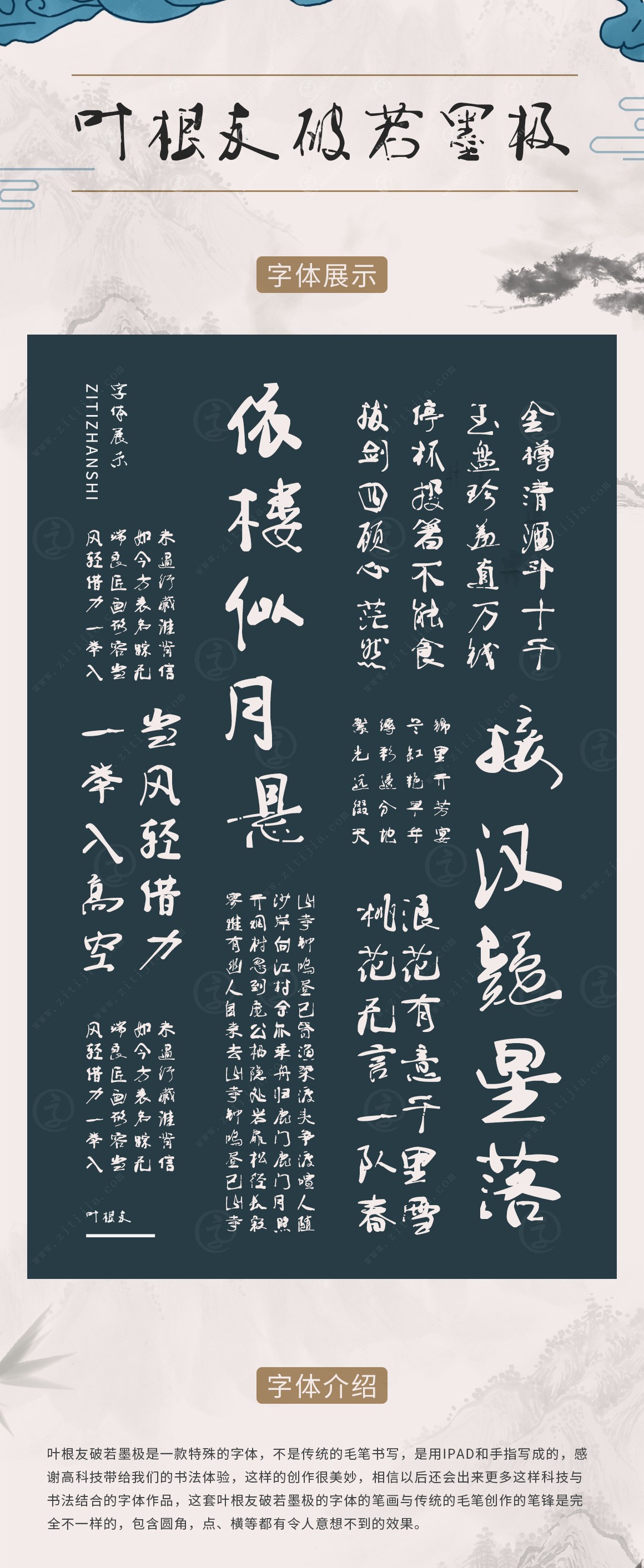
葉根友破若墨極
字體作者:葉根友
創(chuàng)作年代:2016年
字體字?jǐn)?shù):6763個(gè)中文漢字以及其他英文字母和阿拉伯?dāng)?shù)字
字體介紹
葉根友破若墨極是一款特殊的字體,不是傳統(tǒng)的毛筆書寫,是用IPAD和手指寫成的,感謝高科技帶給我們的書法體驗(yàn),這樣的創(chuàng)作很美妙,相信以后還會(huì)出來更多這樣科技與書法結(jié)合的字體作品,這套葉根友破若墨極的字體的筆畫與傳統(tǒng)的毛筆創(chuàng)作的筆鋒是完全不一樣的,包含圓角,點(diǎn)、橫等都有令人意想不到的效果。